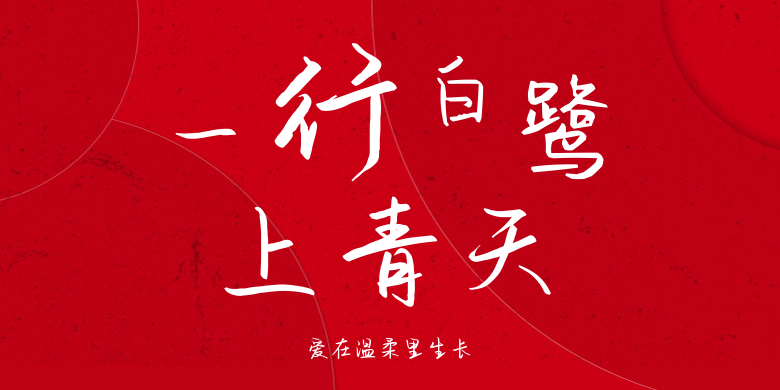
爱在温柔里生长
爱在温柔里生长,这款字体结构工整、笔画清晰,兼顾美观与易读性,适用于标题、正文、海报、包装、LOGO 等多种场景。字形优雅稳定,风格百搭耐看,适配日常排版与创意设计,让文字呈现更舒适、更具质感。爱在温柔里生长一笔一画,皆是细节,以均衡的比例、流畅的线条打造舒适视觉体验,字形端正大气,风格简约现代。无论是商业设计、品牌宣传还是日常排版,都能轻松驾驭,让文字更有格调与力量。爱在温柔里生长字体下载。